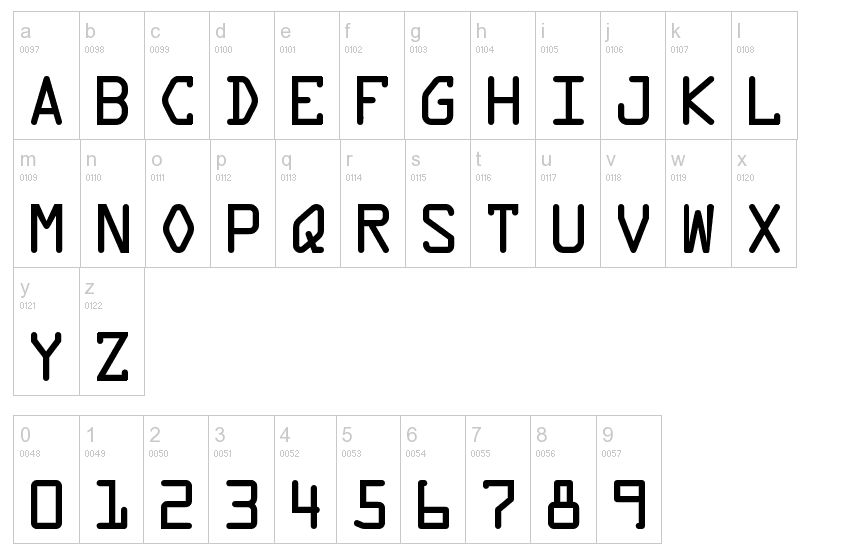
Data Font
Data font đóng vai trò quan trọng trong việc trình bày và trực quan hóa thông tin dữ liệu. Với sự phát triển của công nghệ và nhu cầu ngày càng cao về việc truyền đạt thông tin một cách hiệu quả, việc chọn lựa và sử dụng font chữ phù hợp trở thành yếu tố then chốt. Data font không chỉ là 1 font chữ design giúp tăng tính thẩm mỹ cho các bảng biểu, báo cáo mà còn cải thiện sự dễ đọc và khả năng tiếp nhận thông tin của người xem. Các yếu tố như kiểu dáng, kích thước, và khoảng cách giữa các ký tự đều ảnh hưởng đến trải nghiệm người dùng. Chính vì vậy, hiểu rõ về data font và các yếu tố liên quan sẽ giúp bạn tối ưu hóa việc trình bày dữ liệu một cách chuyên nghiệp và hiệu quả.